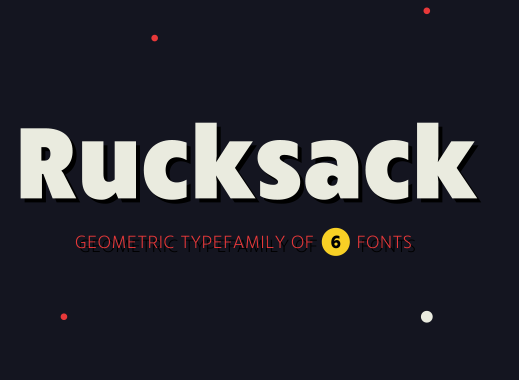
Rucksack é uma família de tipo gótico sans-serif com seis pesos que vão do preto ao leve. Inspirado principalmente no Futura geométrico de Paul Renner dos anos 1920, Rucksack traz formas limpas e amigáveis. Seus traços indentados e x-height alto ajudam a garantir legibilidade ótima. Essa família de tipo é perfeita para uso em papel, especialmente para fins editoriais, mas também funciona muito bem quando usado em ambientes de exposição. Com certeza uma escolha adequada para qualquer projeto visual.